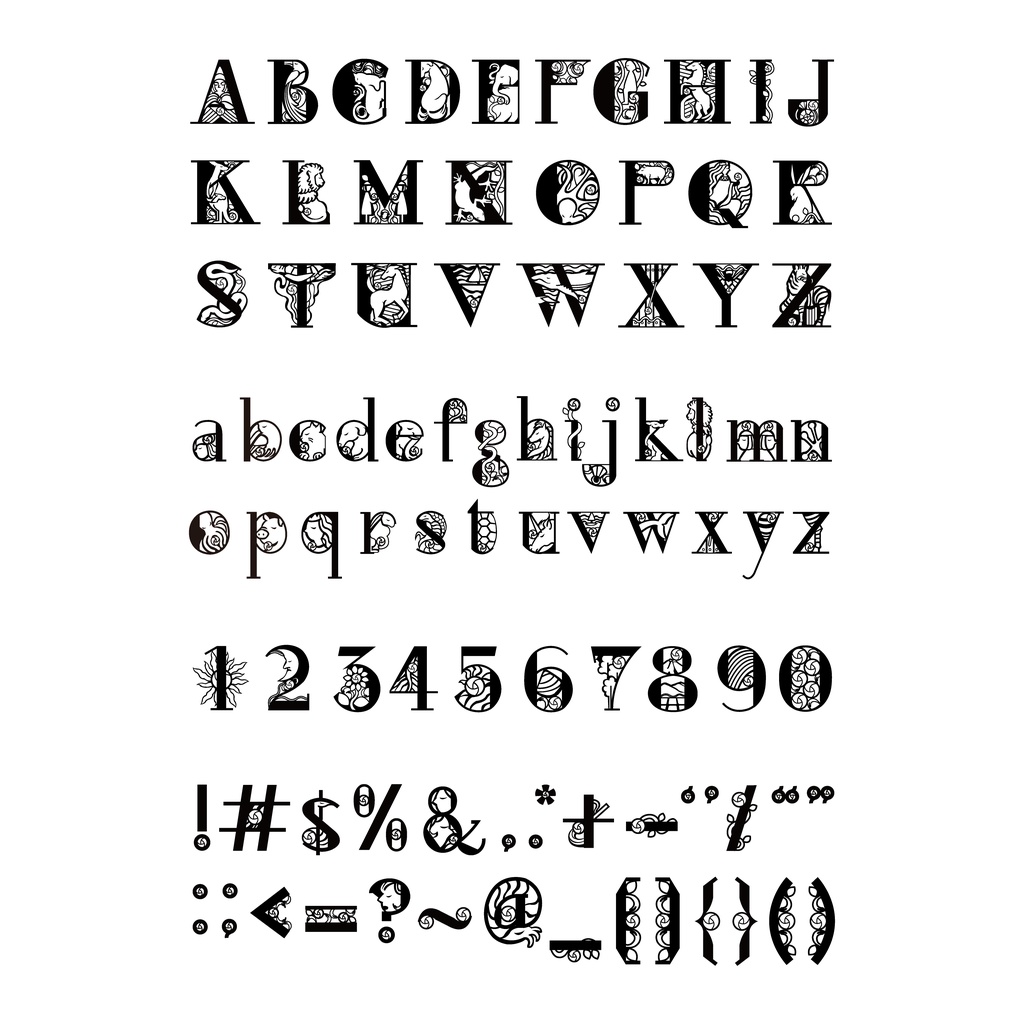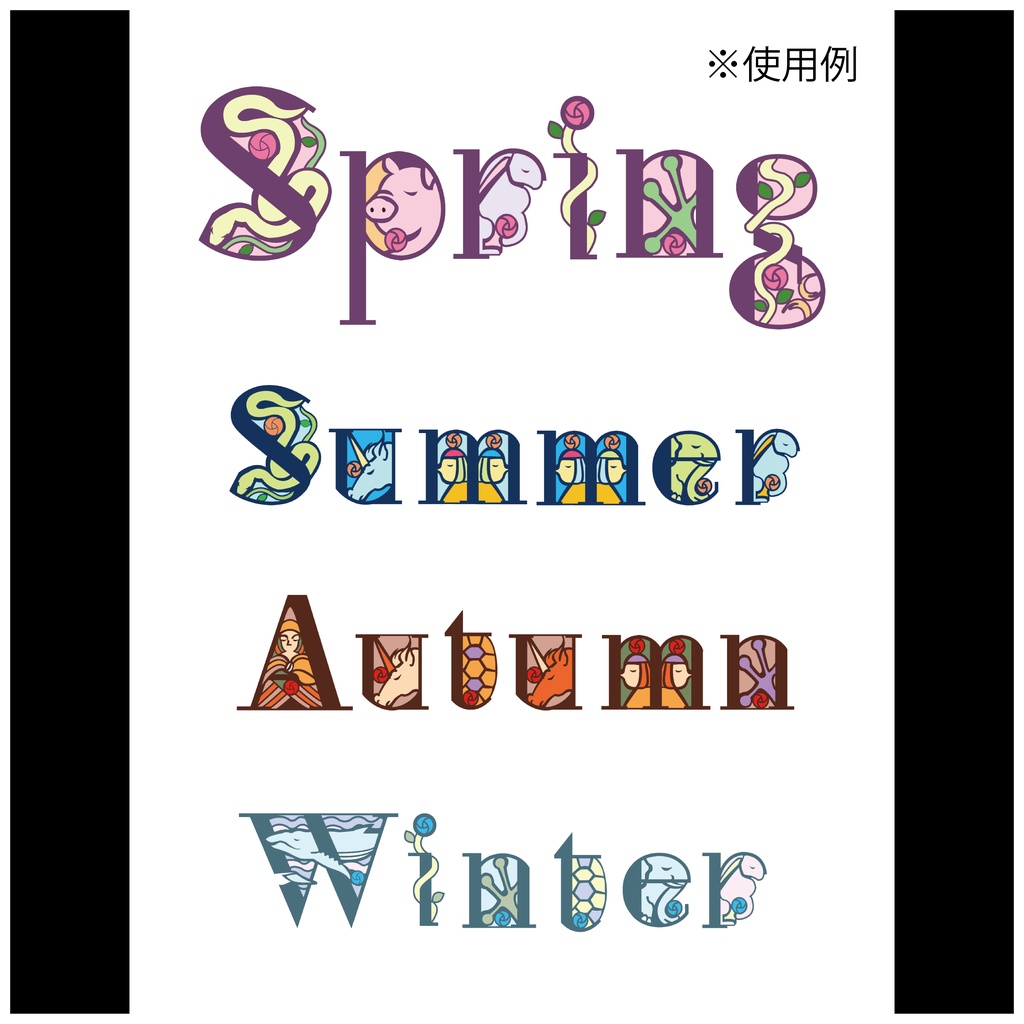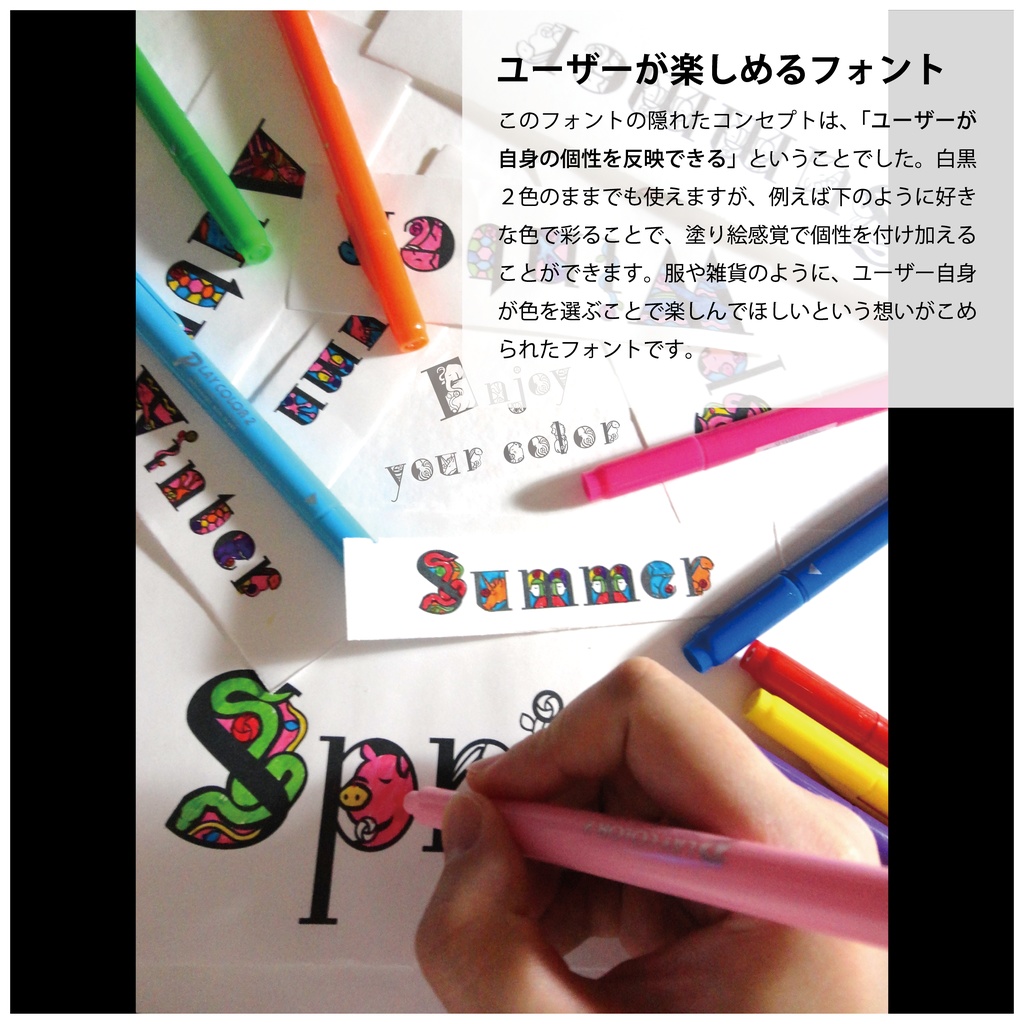
ステンドグラスフォント
⚫︎ユーザーが楽しめるフォント⚫︎ このフォントのコンセプトは「ユーザーが自身の個性を反映できる」ことです。 白黒2色のままでも使えますが、好きな色で彩ることで、塗り絵感覚で個性的なフォントにすることができます。 服や雑貨のように、ユーザー自身が色を選ぶことを楽しんでほしいという想いがこめられたフォントです。 【利用規約】 ・商用・非商用を問わず利用可能です。同人への利用も自由におこなってください。 ・作者は著作権を放棄していません。自作発言はご遠慮ください。 ・当フォントを利用して発生した、いかなる損害についても作者は責任を負いません。 ・フォントデータをダウンロードした時点で利用規約に同意したものとみなします。 【webフォント化、アプリや書籍などへのフォントデータの収録について】 ・サイトへ使用するためのwebフォント化やアプリへの埋め込み、書籍などへのフォントデータの収録を希望される方は、作者までご連絡ください。 ・また同時に、出典の記載をお願いしております。サイト内のどこかにダウンロードページへのリンクをご記載ください。 ・画像化しての使用、フォントデータの配布を伴わない書籍などでの使用については連絡不要です。 【禁止事項】 ・フォントデータの改変・無断転載・再配布・販売 ・当フォントを利用した制作物、ロゴなどの商標登録 【注意事項】 ・ダウンロードデータ内にはotfデータが収録されています。 ・予告なしにバージョンアップを行うことがあります。 ・一部の端末、ソフトウェアでは使用できない場合がございます。